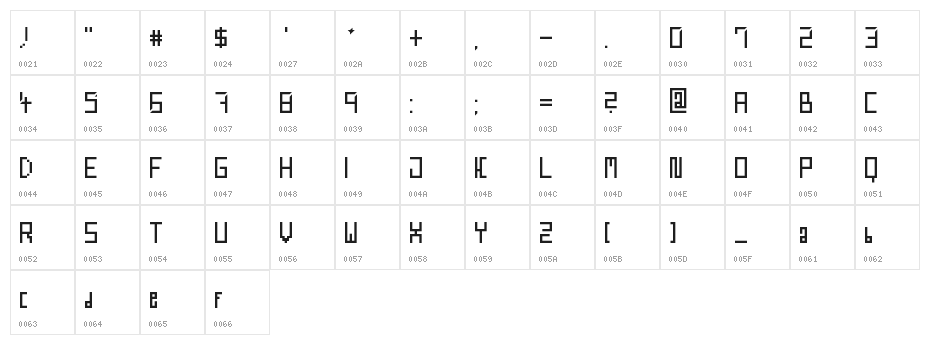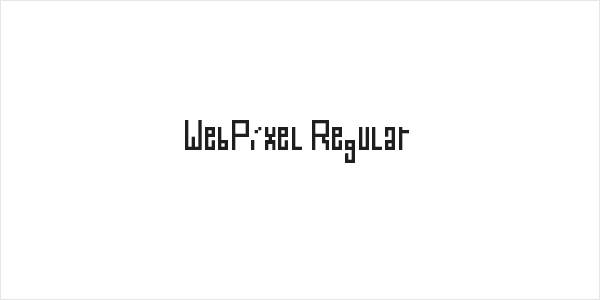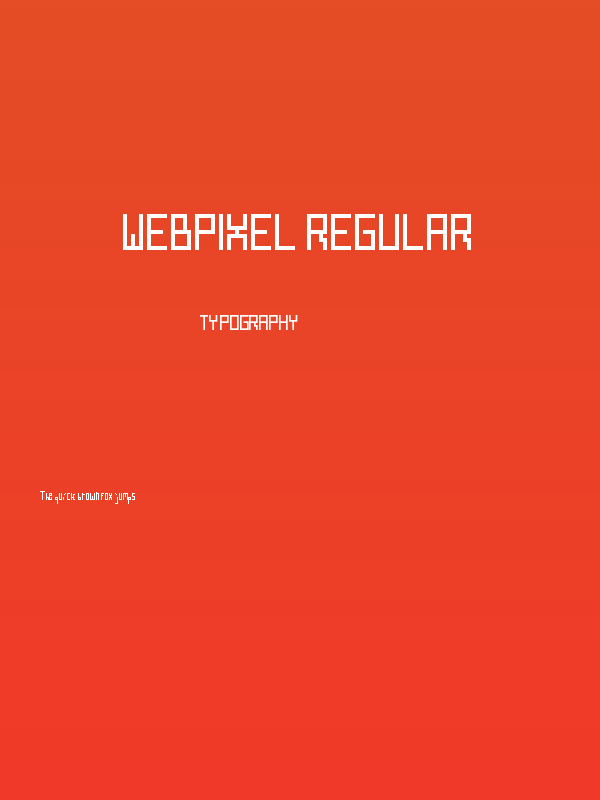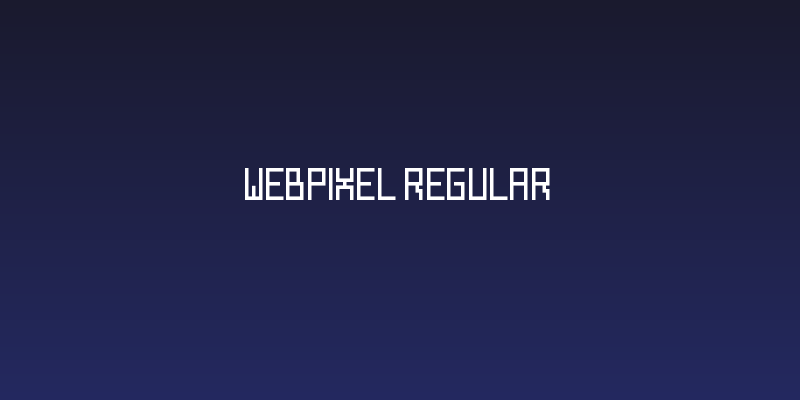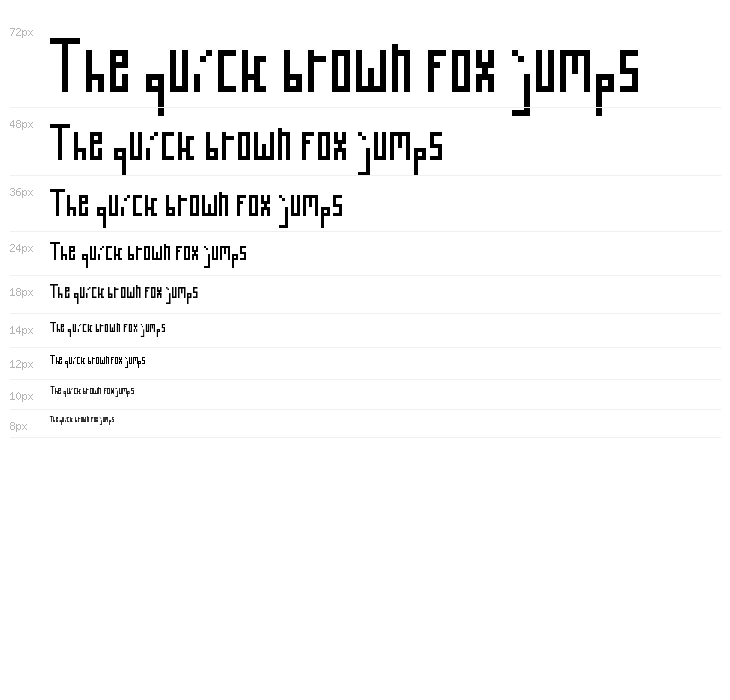
WebPixel Regular Font
✎ Pixel
| Nume | WebPixel Regular |
| Categorii | Pixel |
| Stil general | Vintage, Digital |
| Proiecte propuse | Ideal for retro video games, tech-themed posters, digital art projects, and any design requiring a vintage digital look. |